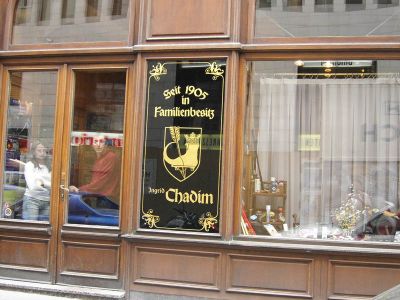
Fraktur und Wissenschaft
in der letzten Ausgabe ›Graphische Revue Österreichs‹ schrieb Christian Gutschi (?) einen Artikel über aktuelle Schrifttrends. Da stand unter Anderem zu lesen, es sei wissenschaftlich belegt, dass Botschaften an gebrochenen Schriften besser haften blieben (mal sinngemäß wiedergegeben).
Was könnte er damit meinen oder kennt gar jemand eine Untersuchung auf die er Bezug genommen haben könnte?
Man kann sehr leicht immer wieder feststellen, daß Gebrochene Schriften Diskussionen auslösen. Diese Schriften sind emotional stark beladen. Sie polarisieren.
Deshalb gibt es auch den Schriftzug des Preußische Bleisatz-Magazin in der Koch-Fraktur. Die Assoziationen mit dem Wort "Preußen" erhöhen diese Polarisierung noch.
Folge: Dadurch ist innerhalb sehr kurzer Zeit gelungen, das PBM als "Marke" einzuführen. Sogar, in einen ja wirklich kleinen Markt, als allgemein bekannte Marke.
Ich stelle mir das immer so vor, daß ein Besucher erst einmal einen Adrenalin-Stoß bekommt, wenn er auf die Seite kommt. "Ne, nä? Das gibt's doch nicht wirklich, oder?" Danach gibt's zwei Möglichkeiten:
a) Er sucht verbissen nach Belegen für seinen "Erstverdacht".
Und findet nichts. Dafür anderes, was diesem eindeutig widerspricht.
b) Sein Nostalgie-Gefühl ist positiv angesprochen und er beginnt, auf der Seite zu stöbern.
Egal - beides ist im Sinne des PBM. Denn in beiden Fällen folgt dann oft auf einer ganz anderen Webseite ein Hinweis auf das PBM. Mit Vermerk "Gugge mol, wie skurril." Oder so. Mit den Adjektiven muß man dann halt auch leben.
Aber so, glaube ich, funktioniert der Einsatz von Gebrochenen Schriften in atypischen Bereichen.
es sei wissenschaftlich belegt, dass Botschaften an gebrochenen Schriften besser haften blieben (mal sinngemäß wiedergegeben).
Such doch nochmal den Original-Wortlaut raus, und vor allem, ich welchem Zusammenhang das stand. Ansonsten ist doch alles spekulativ.
Georgs Deutung ist nur eine von vielen Möglichkeiten. Es könnte auch eine »alte« Aussage aus den Zeiten des Fraktur-Antiqua-Streites sein.
Man könnte genauso dagegen argumentieren: Wenn ich einem jüngeren Menschen heute einen Text in gebrochenen Schrift vorlege, bleibt überhaupt nichts »haften«, weil es überhaupt keiner mehr lesen kann.
Wenn ich dran denk, werd ich zu Mittag das Heft wegen des exakten Wortlautes mit nehmen. Mehr als mein sinngemäßes Zitat ist daraus aber echt nicht zu entnehmen. Kennt hier jemand diesen Christian Gutschi? Vielleicht kann er ja eine Stellungnahme dazu abgeben. Leider war beim Artikel keine E-Mail verzeichnet.
Graphische Revue Österreichs, 2004/6
Cristian Gutschi:
»Revival der Frakturschriften: Die gebrochenen Schriften waren wegen ihrer kurzen Verwendung im Nazireich verpönt — nur internationale Zeitungsköpfe und gemütliche Eckkneipen verwendeten diesen Schrifttypus, von dem es mittlerweile mehr als 300 verschiedene digitale Fonts gibt. Doch vor Kurzem kam der Schuhhersteller Nike — in der folge auch Reebok und sogar Designer wie Joop! — auf die Fraktur. Passend zum Hype, erschien kürzlich das herausragende Buch ›Fraktur mon amour‹ — das erste Kompendium digitaler Frakturschriften. Bei der heutigen Jugend gilt der Formenreichtum der bildhaften Schriftzeichen als ›cool‹, und es sieht danach aus, dass Frakturschriften nun immer häufiger verwendet werden. Schließich konnte wissenschaftlich belegt werden, dass an den differenzierten Buchstabenformen der Fraktur besser haften bleiben als an den grundlegend abstrakten formen klassischer Groteskschriften. Und wer ein Joop!-Shirt mit Fraktur trägt, leistet einen wichtigen Beitrag zur Ehrenrettung der gebrochenen Schriften, indem deren konnotierte Schriftgeschichte ausgelöscht und in einen neuen Kontext gestellt wird.«
> Schließich konnte wissenschaftlich belegt werden, dass an den differenzierten Buchstabenformen der Fraktur besser haften bleiben als an den grundlegend abstrakten formen klassischer Groteskschriften.
hmm, wissenschaftlich belegt – so, so ... wo denn? würde mich mal interessieren, schreib doch mal den autor an.
"dass an den differenzierten Buchstabenformen der Fraktur besser haften bleiben" ähm, was bleibt haften?
Dann hat es Georg ja mit seiner Deutung doch recht gut getroffen. Allerdings trifft das ja nicht nur auf gebrochene Schriften zu, sondern auf alle möglichen Display-Typen, die sich von den glatt-gelutschten Frutiger-Klonen abheben. Ich denke da zum Beispiel an Schriften wie Farao oder Salmiak. Bei solchen Schriften bleibt man wirklich buchstäblich eher »hängen« als bei irgendeiner Grotesk. Wenn man im Supermarkt den Blick über ein Regal schweifen lässt, bemerkt man diesen Effekt deutlich.
Ja. Diese Deutung hat was. Allerdings sehe ich daran nicht, dass an der Schrift eine Botschaft hängen bleibt — indem ich meine Botschaft quasi drauf stecken kann und die Schrift als Transprotcontainer fungiert —, sondern dass sie eine Botschaft in sich beinhalten (oder darstellt) und viel mehr der Betrachter an der ›ungewohnten‹ Form hängen bleibt.
Ich hab den Autor mal angeschrieben und warte jetzt auf eine Antwort.
Was ich persönlich ganz wichtig finde:
@ Willi
Und, kommst de klar mit den vier s?
S, s (rund-s), ſ (lang-s, mit Alt + 383) und ß?
Neue oder alte Rechtschreibung?